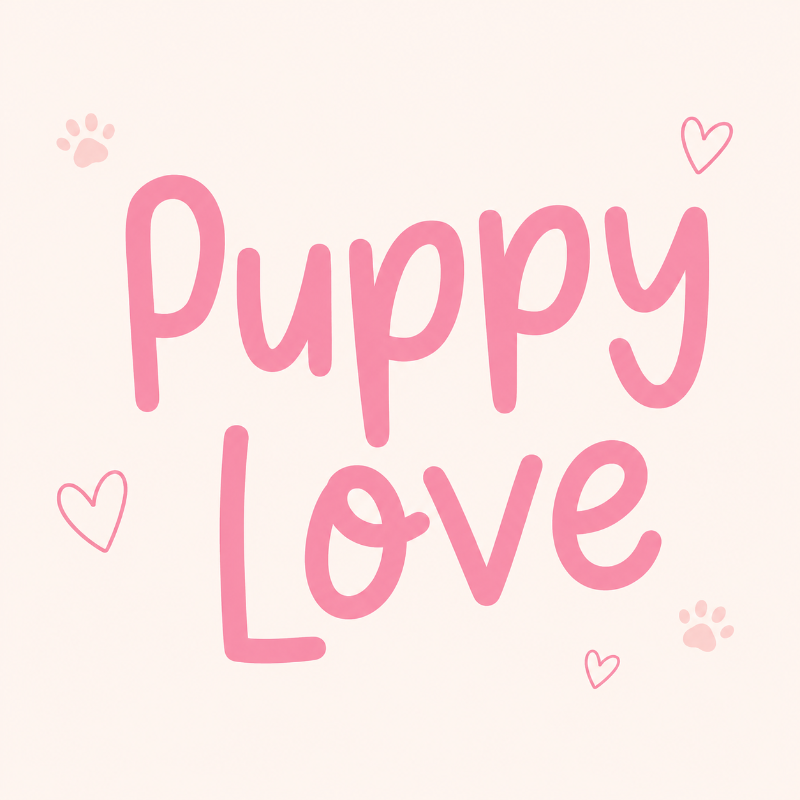
Bạn đã từng nhìn một thiết kế và thấy bố cục, màu sắc, hình ảnh đều ổn, nhưng tổng thể vẫn thiếu cảm xúc? Vấn đề có thể nằm ở typography. Một font chữ viết tay phù hợp có thể giúp thiết kế trở nên mềm mại, gần gũi, nghệ thuật hoặc cá tính hơn. Đây là điều mà nhiều font chữ truyền thống như Serif hay Sans-Serif đôi khi khó tạo ra.
Tuy nhiên, với designer Việt Nam, khó khăn không nằm ở việc tìm font đẹp. Khó nhất là tìm được font viết tay Việt hóa đầy đủ dấu tiếng Việt. Nếu font không hỗ trợ các ký tự như “á”, “ồ”, “ế”, “ữ”, thiết kế rất dễ bị lỗi chữ, mất thẩm mỹ và thiếu chuyên nghiệp.
Bài viết dưới đây sẽ tổng hợp hơn 20 font chữ viết tay Việt hóa đẹp, được phân loại theo từng phong cách thiết kế. Nhờ đó, bạn có thể chọn nhanh font phù hợp cho poster, logo, thiệp mời, banner, bài đăng mạng xã hội hoặc các dự án sáng tạo khác.
Vì sao Font chữ viết tay lại trở thành xu hướng không thể thiếu?
Font chữ viết tay trở thành xu hướng vì nó mang lại cảm giác gần gũi, tự nhiên và giàu cảm xúc trong thiết kế. Giữa rất nhiều kiểu chữ kỹ thuật số chỉn chu, font viết tay tạo nên dấu ấn riêng, giống như nét bút thật của con người. Chính sự mềm mại, ngẫu hứng và đôi khi không hoàn hảo này lại giúp thiết kế trở nên chân thực hơn.
Không chỉ đẹp về mặt thẩm mỹ, font viết tay còn có tính ứng dụng rất cao. Bạn có thể bắt gặp kiểu chữ này trên thiệp cưới, menu quán cafe, bao bì sản phẩm thủ công, poster nghệ thuật hoặc các câu quote truyền cảm hứng trên mạng xã hội. Nhờ khả năng truyền tải cảm xúc tốt, font viết tay giúp nội dung trở nên nổi bật và dễ chạm đến người xem hơn.
Top 20+ font chữ viết tay Việt hóa đẹp nhất theo từng phong cách
Bạn không cần mất thời gian lướt qua hàng loạt font chữ rồi phân vân không biết nên chọn loại nào. Cách nhanh nhất là xác định trước phong cách thiết kế bạn đang cần, sau đó chọn font phù hợp với tinh thần của dự án. Dưới đây là những font chữ viết tay Việt hóa nổi bật, được phân loại theo cảm xúc, độ ứng dụng và phong cách thể hiện.
MTD Great Vibes
MTD Great Vibes là lựa chọn phù hợp cho những thiết kế cần sự mềm mại, bay bổng và tinh tế. Font có đường nét uốn lượn đẹp, độ thanh đậm rõ ràng, tạo cảm giác sang trọng ngay từ cái nhìn đầu tiên. Bạn có thể dùng MTD Great Vibes cho thiệp cưới, logo thương hiệu cao cấp, tiêu đề poster hoặc các ấn phẩm mang hơi hướng lãng mạn.
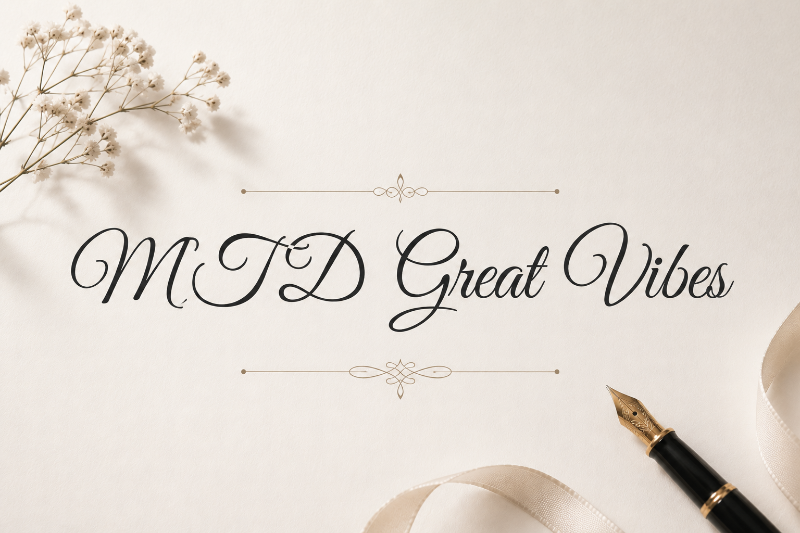
SVN Betalisa
SVN Betalisa gây ấn tượng nhờ nét chữ thanh mảnh, nữ tính nhưng vẫn rất sắc sảo. Font này giống như một chữ ký cá nhân đầy tự tin, phù hợp với các thiết kế dành cho thời trang, mỹ phẩm, spa, beauty salon hoặc thương hiệu cá nhân. Nếu bạn muốn tạo cảm giác hiện đại, tinh tế và có chút kiêu hãnh, SVN Betalisa là một lựa chọn đáng cân nhắc.
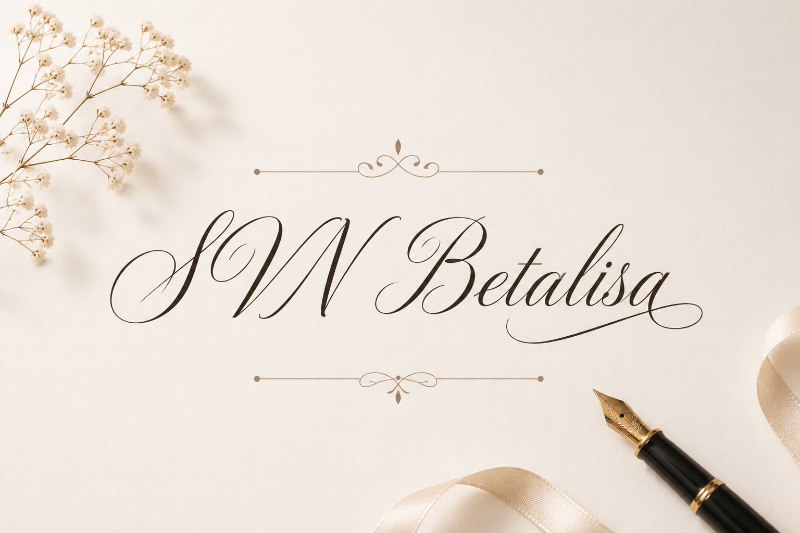
TH Signatura
TH Signatura mang phong cách sang trọng, cân đối và có tính nhận diện cao. Đây là font viết tay rất phù hợp khi dùng làm điểm nhấn chính trong logo, bộ nhận diện thương hiệu hoặc các thiết kế cần cảm giác chuyên nghiệp. Nét chữ của TH Signatura không quá rối, đủ mềm mại nhưng vẫn giữ được sự rõ ràng và cao cấp.
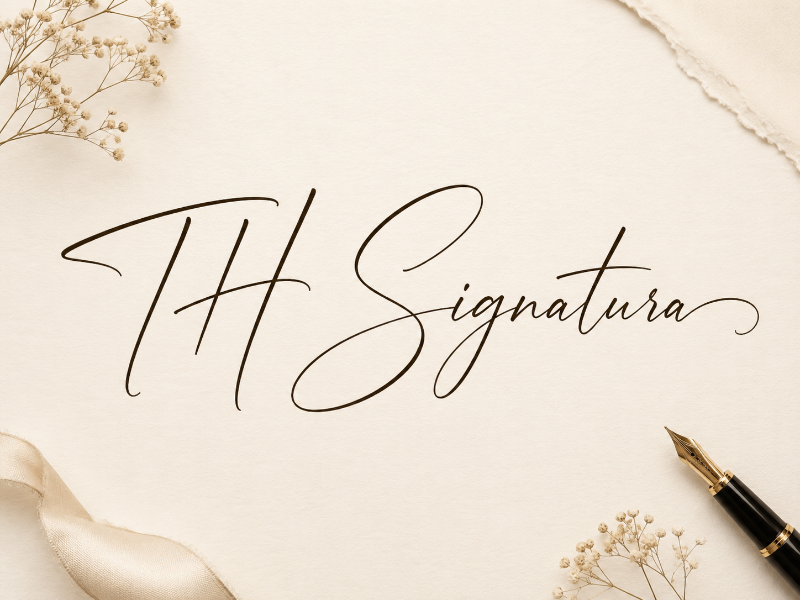
Satisfy
Satisfy là font chữ viết tay có cảm giác tự nhiên, gọn gàng và dễ đọc. Chiều cao chữ vừa phải giúp font này hiển thị tốt ngay cả khi dùng ở kích thước nhỏ. Vì vậy, Satisfy phù hợp cho tiêu đề phụ, quote ngắn, banner, bài đăng mạng xã hội hoặc các thiết kế cần sự thân thiện nhưng không quá cầu kỳ.
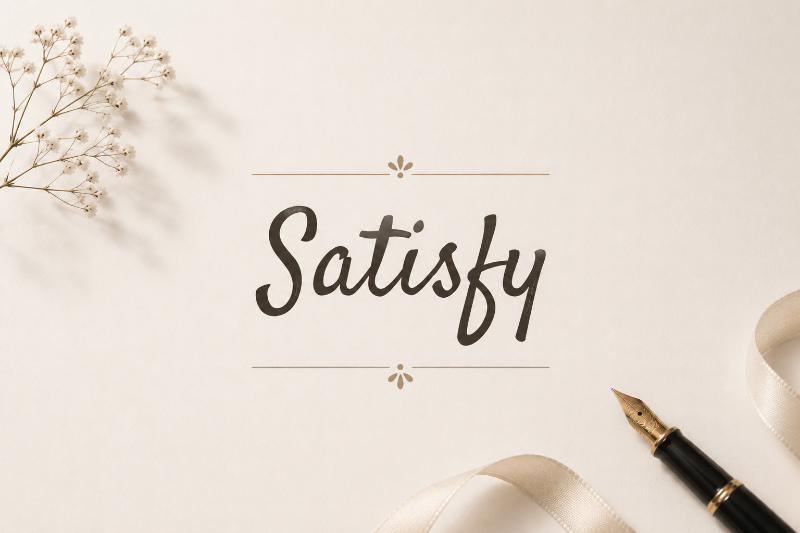
Pacifico
Pacifico mang đến cảm giác trẻ trung, phóng khoáng và hiện đại. Nét chữ mềm mại nhưng không quá nữ tính, tạo được sự vui tươi và gần gũi. Font này rất hợp với các thiết kế về du lịch, đồ uống, thời trang trẻ, blog cá nhân, poster sự kiện hoặc những ấn phẩm cần một chút hơi thở phương Tây.
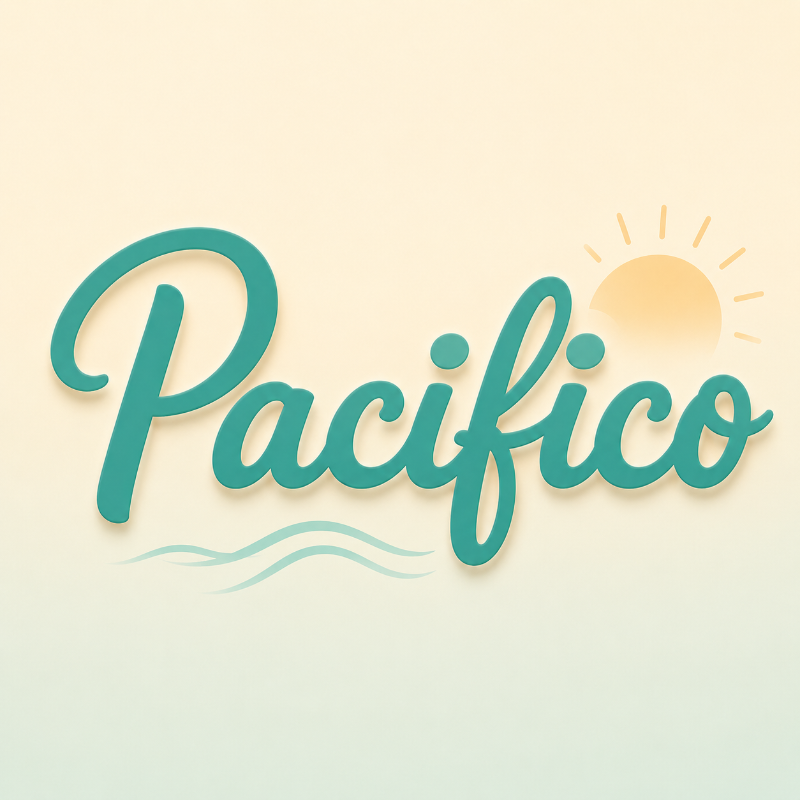
UTM Ông Đồ Già
UTM Ông Đồ Già là font chữ mang đậm tinh thần thư pháp truyền thống Việt Nam. Nét chữ gợi cảm giác hoài cổ, trang trọng và rất gần với không khí văn hóa Á Đông. Đây là lựa chọn gần như không thể thiếu cho các thiết kế dịp Tết Nguyên Đán, Trung Thu, lễ hội dân gian, câu đối, thiệp chúc mừng hoặc các ấn phẩm mang màu sắc truyền thống.
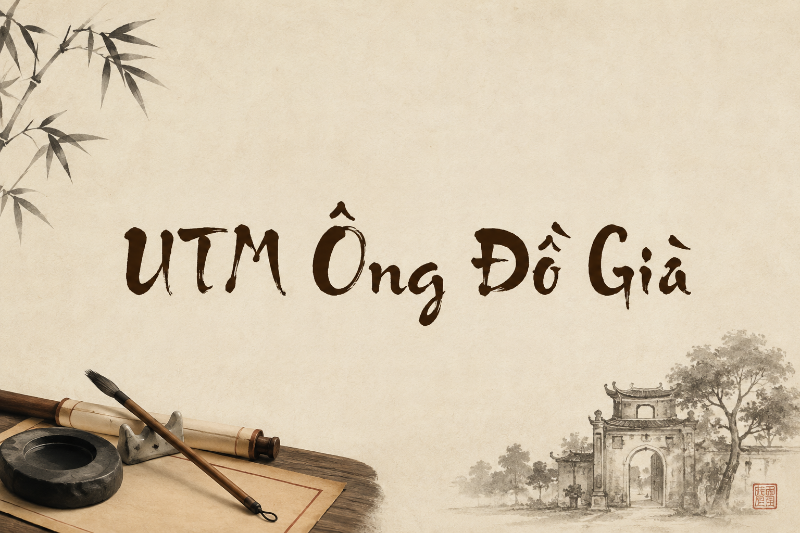
Clementi
Clementi sở hữu nét chữ mềm mại, hơi nghiêng nhẹ, tạo cảm giác giống như những bức thư tay đầy cảm xúc của thập niên cũ. Font này phù hợp với các thiết kế cần sự lãng mạn, tinh tế và có chiều sâu cảm xúc. Bạn có thể dùng Clementi cho thiệp mời, quote tình cảm, poster nghệ thuật hoặc các ấn phẩm mang phong cách vintage.
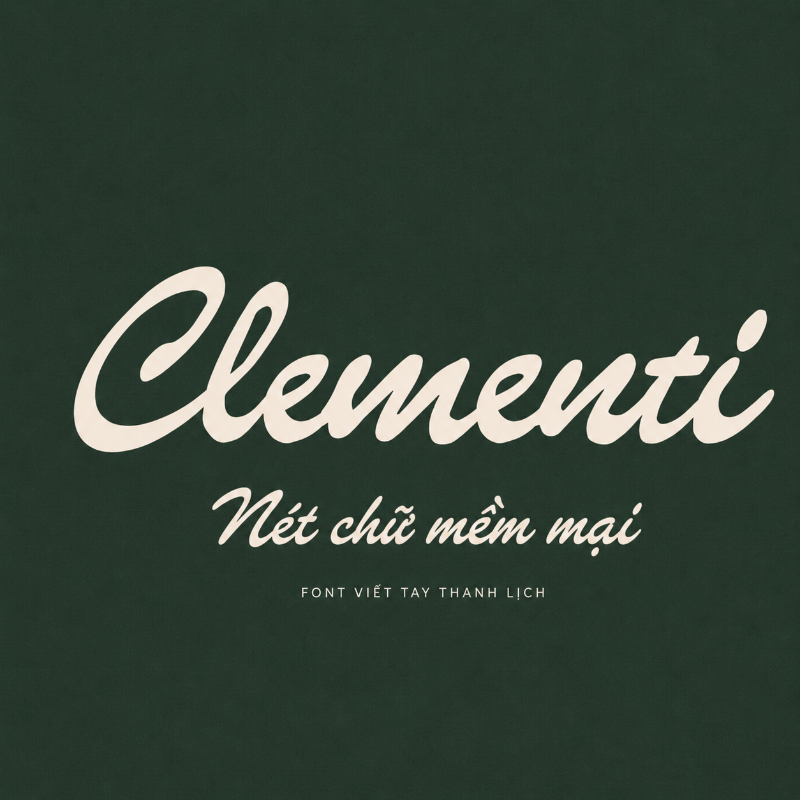
Grand Estonia
Grand Estonia mang vẻ đẹp thanh lịch, cổ điển và có phần quý tộc. Nét chữ gợi liên tưởng đến các ấn phẩm châu Âu xưa, nơi sự chỉn chu và tính thẩm mỹ được đặt lên hàng đầu. Font này rất phù hợp với thiết kế bao bì cao cấp, logo thương hiệu, thiệp trang trọng hoặc các dự án cần cảm giác lịch sử, sang trọng và tinh tế.
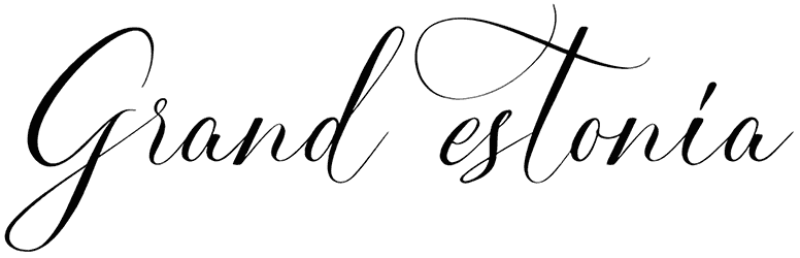
Kristian Paradise
Kristian Paradise có phong cách cổ điển, mộc mạc và giàu chất hoài niệm. Font không quá phô trương mà tạo cảm giác nhẹ nhàng, trầm lắng và gần gũi. Đây là lựa chọn phù hợp cho các thiết kế về thủ công, cà phê, sách, nhật ký, phong cách vintage hoặc những ấn phẩm cần truyền tải sự dung dị và tĩnh lặng.
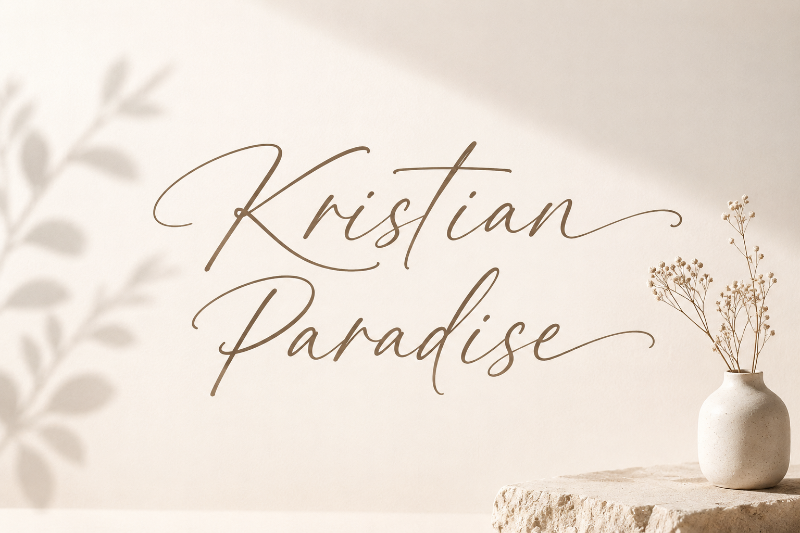
Sở hữu một bộ font chữ đẹp chính là lợi thế lớn giúp designer sáng tạo nhanh hơn và tạo dấu ấn riêng trong từng thiết kế. Hy vọng bộ sưu tập 20+ font chữ viết tay Việt hóa được chọn lọc và phân loại ở trên sẽ giúp bạn dễ dàng tìm được kiểu chữ phù hợp cho từng ý tưởng